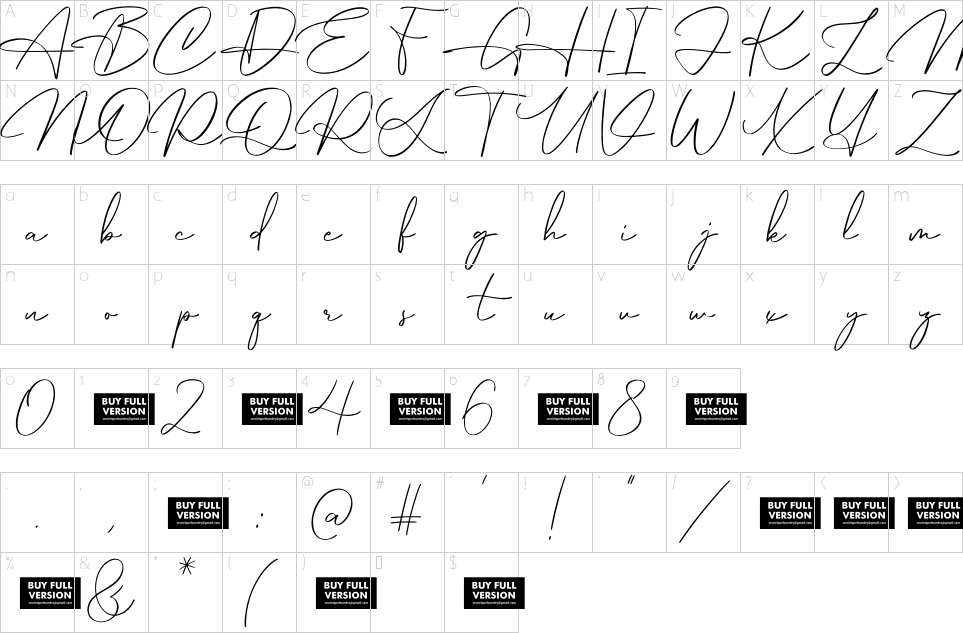
Hamburg Signature Font – Download Grátis
Descubra a delicada elegância do Hamburg Signature Font para suas criações digitais. Desenvolvida pela Anxietype Foundry, esta fonte tem sido uma escolha popular entre designers que valorizam um ar de sofisticação e contemporaneidade em seus projetos. Com sua configuração limpa e agradável aos olhos, o Hamburg Signature é perfeito para texturas semelhantes ao texto corporativo ou design editorial. Desfrute da versatilidade desta fonte, que pode ser utilizada tanto no Windows quanto na Mac. Seja você um iniciante ou um profissional experiente, a Hamburg Signature oferece uma maneira elegante de adicionar um toque único à sua identidade visual. A fonte já foi baixada 865 vezes e continua sendo uma opção popular para quem busca não apenas beleza, mas também versatilidade em suas criações digitais.